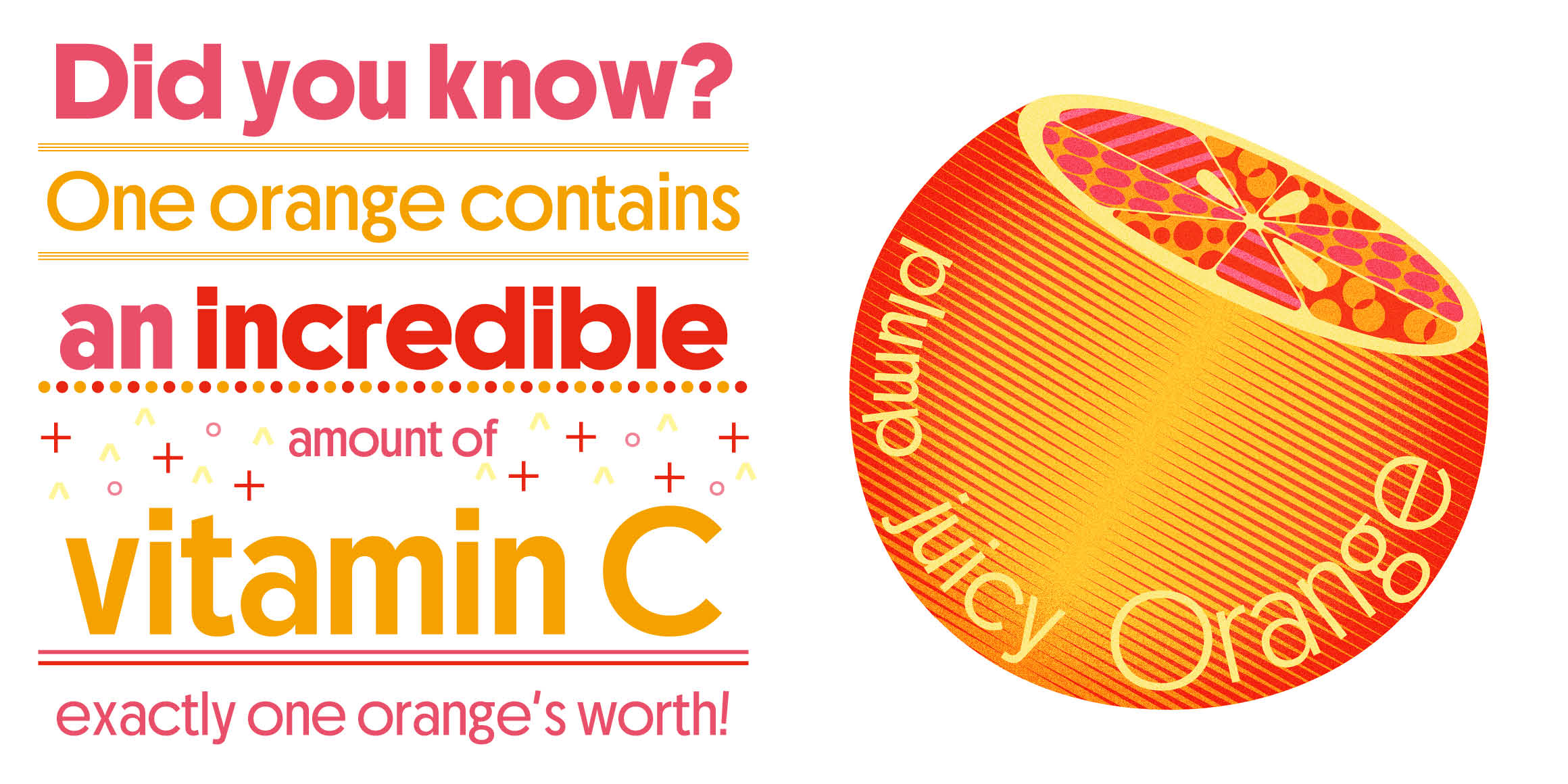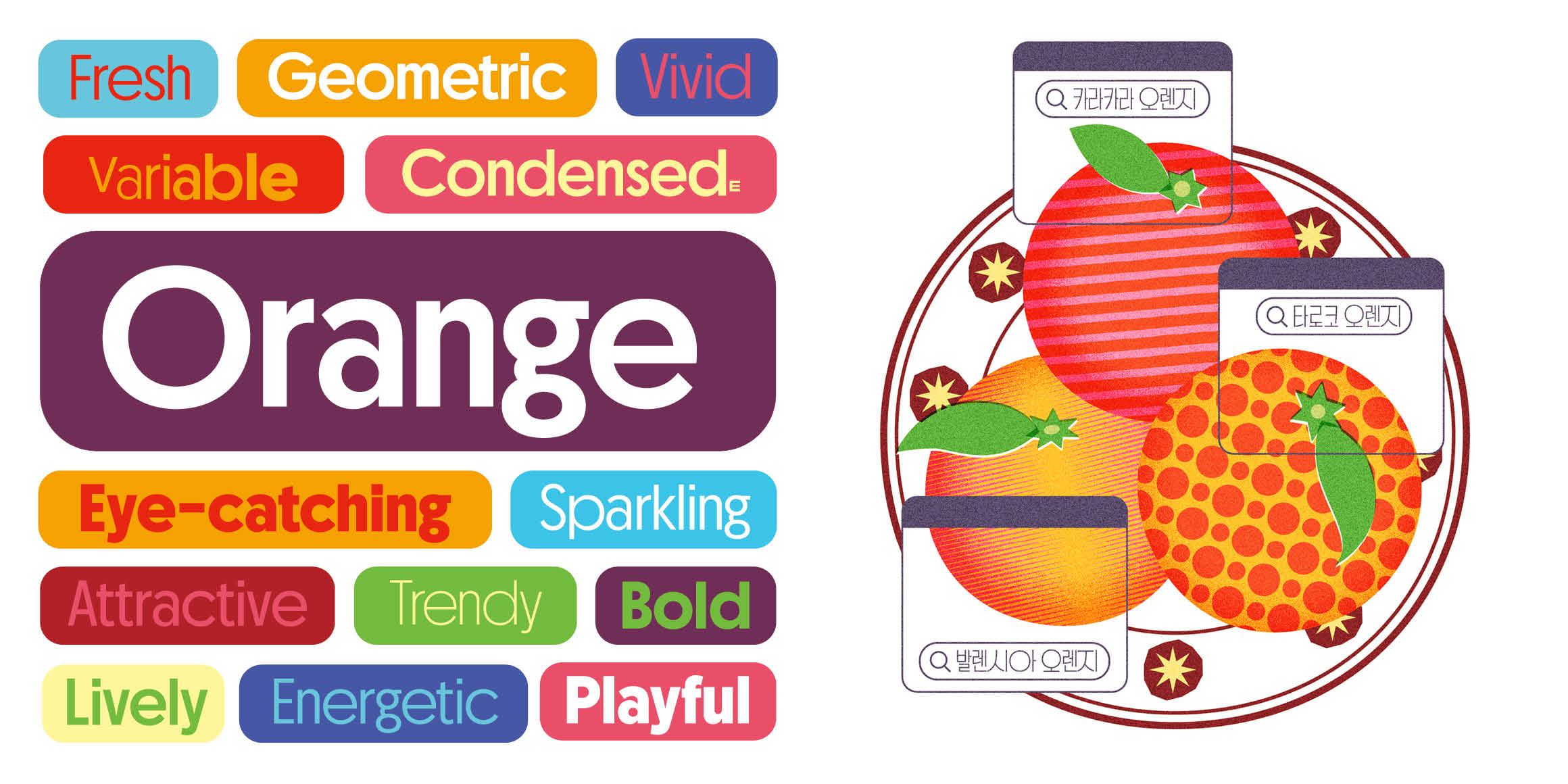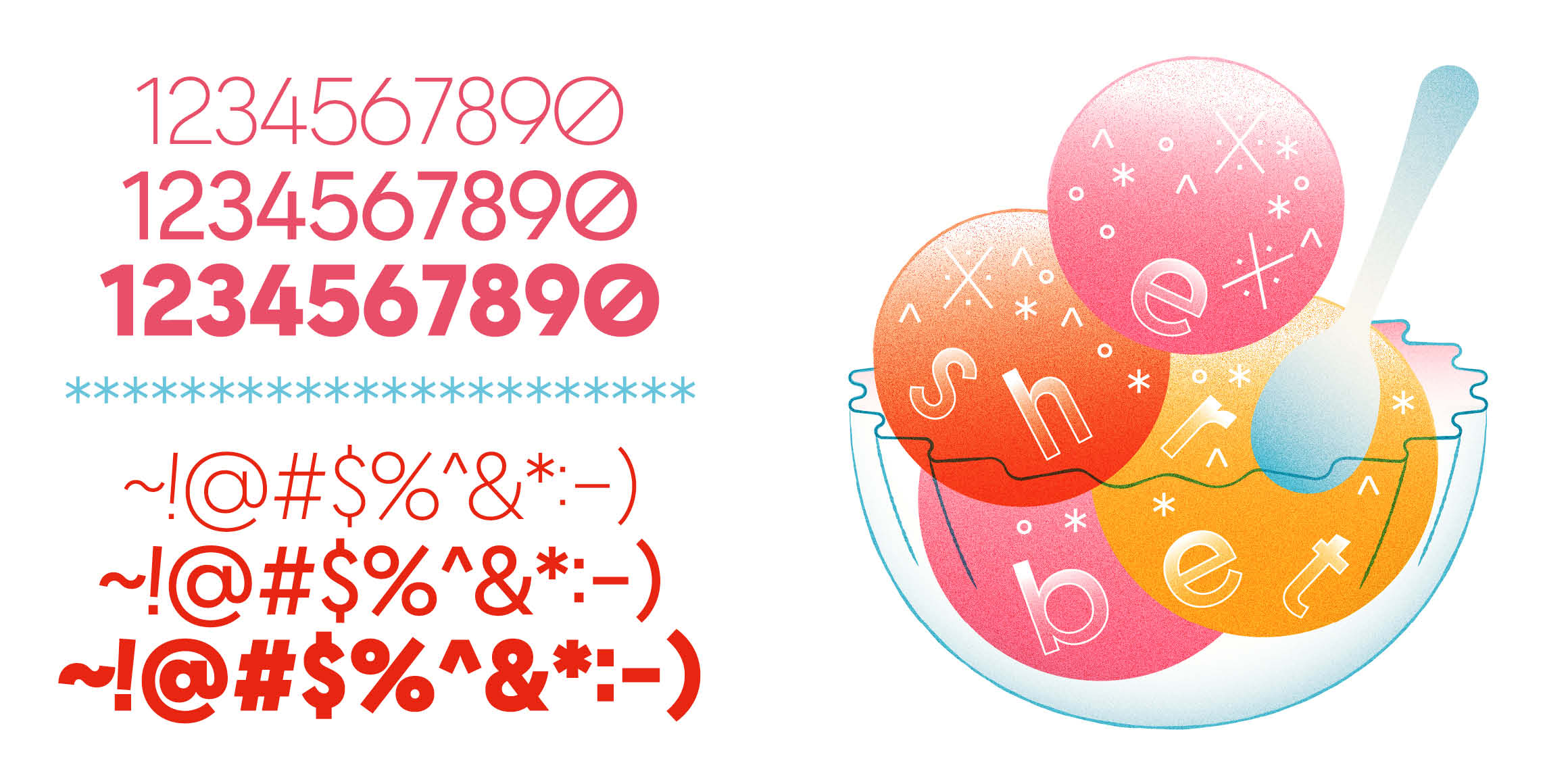
오렌지 Latin
Jeong Hyunah
‘오렌지 Latin’은 서체 ‘오렌지’에서 영문만을 포함한 폰트입니다. 꽉 찬 모듈 안에서 원을 최대한 크게 그려 귀여움과 지오메트릭함을 강조했습니다. 원의 크기에 따라 폭이 변하는 것이 가장 큰 특징입니다.
• 정현아
• 오렌지 Latin / Orange Latin